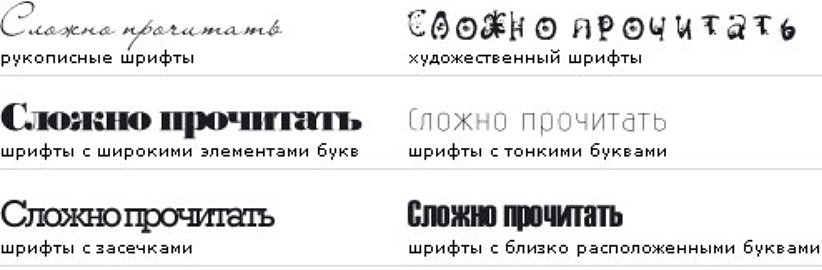
Хладнокровный бизнесмен, всеми любимый офисный пухляш, уставшая домохозяйка, кайфовый и чилловый сёрфер?
Визуализация образа шрифта помогает нам уловить ритм речи, посылы, тон, громкость голоса и заявлений бренда.
Где он?
Нужно понять, в какой окружающей среде находится бренд. Если это деловая среда, где строгие дяденьки каждый день управляют миллиардами денег, то милые шрифты с завитушками тут не в тему.
Слайд презентации Миши.Если мы говорим о сказочном мире магии, где есть маглы, старые магические замки, дементоры и оборотни, то почему бы шрифту не подстроиться и не быть немного сказочным?
Помните шрифт из Гарри Поттера? Объективно, вроде не оч, но для такого сказочного мира очень даже оч.
Какой он?
Слайд презентации Миши. Вариант сочетания шрифтов подобран им.Исходя из предыдущих пунктов, нужно определить, какой характер у персонажа. Если мы строим типографику для бренда удобной офисной мебели, то у нас вполне может быть образ милого офисного пухляша, мягкого, добродушного и весёлого.
От него всегда веет теплотой и свежими пончиками.
Какая у него задача?
Слайд презентации Миши.Далее мы определяемся с задачей шрифта. Этот добродушный пухляш всех успокаивает? Весело шутит? Приободряет?
Если решить, какие задачи должен выполнять шрифт, то окончательно становится понятно, как он должен выглядеть.
Непоколебимый опытный деловой чел говорит болдовым гротеском в верхнем регистре.
Шрифт, соответствующий деловому челу.Добрый офисный пухляш говорит закруглённым болдовым шрифтом с заглавной буквой в нижнем регистре, чтобы не повышать тон.
Шрифт, соответствующий офисному пухляшу.Вопросы к шрифту
Однажды я вёл работу над айдентикой онлайн-школы подготовки к ЕГЭ по Физике. Нужно было выделиться от конкурентов современным необычным стилем, в какой-то степени даже экстравагантным.
После анализа ТЗ я понимал, что логотип будет текстовым, поэтому акцидентному шрифту нужно уделить особое внимание, потому что он будет в логотипе, то есть везде.
По всем советам из лекции выше я расписал в Miro карту шрифтов, получилась такая схема (см. ниже). Этим способом я пользуюсь до сих пор.
Далее я стал искать нужные по духу шрифты (о сервисах, где искал — в конце статьи).
Акцидентный
Его задачи: зацепить и заявить о себе. Нужно что-то неординарное и необычное. Helvetica, Roboto или Montserrat тут нам не помогут, поэтому пришлось немного постараться. В итоге я нашёл, что искал.
Как подобрать правильный шрифт для своего дизайна
Дизайнеры очень часто не уделяют должного внимание типографике, когда на самом деле — это очень важный аспект, от выбора которого нередко зависит качество дизайна. Шрифты так же важны для веб-сайта, как и изображения.
Типографика — это не просто выбор шрифта. Это также этап, на котором необходимо задумать о кернинге, трекинге и интерлиньяже. Частью типографики также является выбор цвета текста, расположение текста и даже дизайн страницы.
Эффективность сообщения, которое вы хотите передать своим сайтом, часто зависит от выбора гарнитуры.
Хороший шрифт завлекает зрителя и влияет на его восприятие идеи.
Хорошо подобранный шрифт помогает зрителю получать удовольствие от чтения. Необходимо всегда выбирать шрифт к подходящей ситуации.
Выбор правильной гарнитуры также усложняется тем, что доступных для использования шрифтов очень много. Нельзя сказать, что есть какое-то определенное правило, помогающее подобрать правильный шрифт во всех случаях, но есть некоторые принципы, которые могут быть использованы в самых различных ситуациях и достойны дополнительного внимания.
Разборчивость очень важна
Для того, чтобы читающий мог понимать о чем идет речь, очень важно чтобы гарнитура была разборчивой. Существует множество факторов, которые необходимо учитывать, когда дело касается разборчивости текста. Эти факторы включают в себя размер, форму и ширину символов, визуальный веc, надстроечную и подстрочную длину, а так же контрастность штриха. Выбор качественного шрифта – хорошее начало для создания разборчивого текста, но из-за огромного количества различных шрифтов выбор сделать может быть очень непросто.
Определенные элементы текста могут показаться посетителям сайта выделенными, если изменить высоту или визуальный вес шрифта. Helvetica Neue например имеет не только жирный и курсивный, но и тонкий и ультра-тонкий. Такие шрифты очень полезны, если хочется сделать дополнительный акцент на гарнитуре сайта.
Самые понятные шрифты — те буквы у которых имеют привычную форму и общее характеристики которых наиболее постоянны. Для того чтобы шрифт казался пропорциональным приходится регулировать расстояние между символами – этот процесс называет кернингом. Таким образом улучшается вид шрифта в целом.
Качественные гарнитуры всегда разбиты на керн-пары позволяющее легко достигнуть нужного эффекта. Расстояние между буквами очень влияет на разборчивость шрифта, поэтому шрифты со слишком большими расстояниями между символами стоит избегать.
Некоторые из самых известных шрифтов с засечками включают Times New Roman и Georgia.
Шрифт Times New Roman, в частности, подпадает под категорию классических веб-шрифтов . В целом, вы не ошибетесь, выбрав типы шрифтов по умолчанию, такие как этот, поскольку они обычно легко читаются и существуют уже давно, поэтому многие пользователи Интернета привыкли к ним.Тем не менее, если вы предпочитаете более смелый подход, мы рекомендуем попробовать такие шрифты, как Noe Display, Freight Text или Коллекция Portrait. Конечно, всегда есть шрифты с засечками Google, которые вы можете использовать бесплатно, например Playfair Display, Cormorant Garamond или Crimson Text и многие другие.